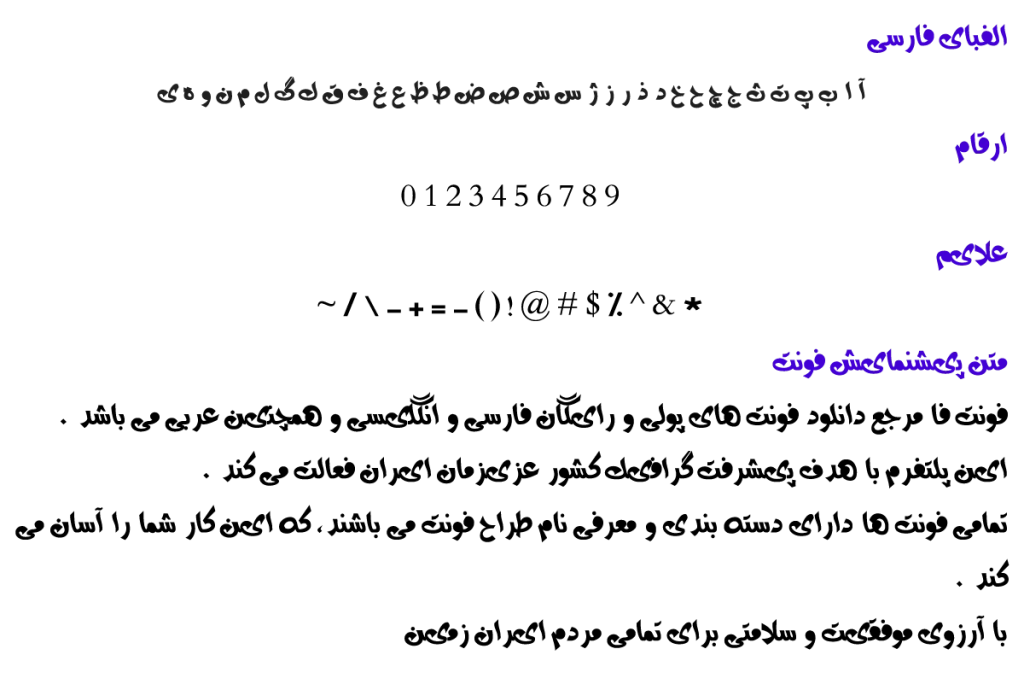
فونت فارسی نصر – Mj Nasr
مجموعه فونت: فونت سری Mj
طراح فونت: مجتبی کیا نوع فونت: فونت گرافیکی
توضیحات و معرفی فونت نصر
فونت فارسی نصر ( Mj Nasr ) از مجموعه فونت های سری Mj می باشد، و نیز نوع فونت گرافیکی می باشد.
فونت خوشگل مربوط توسط مجتبی کیا در سال 1390 طراحی و ساخته شده است.
و نیز فونت Mj Nasr در یک وزن پر رنگ است.
- Mj Nasr Bold
نگاهی بیندازید به تصویر زیر که نمونهای از این تایپ فیس را در شعر «وطن» نمایش می دهد.